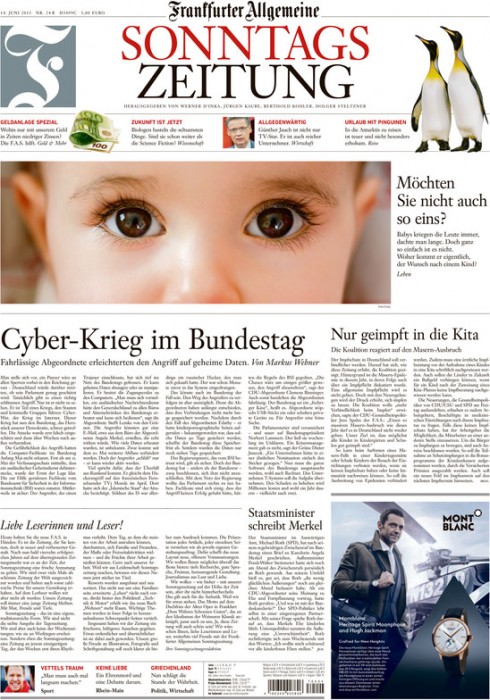
»Herrschaftliche Serifen« – neues Layout der FAS
Neues Layout bei der FAS
»Herrschaftliche Serifen« nennt die Süddeutsche online das, was das neue Layout der Frankfurter Allgemeine Sonntagszeitung ausmacht. Dieses stellte sich mit der heutigen Ausgabe zum ersten Mal dem kritischen Blick seiner Leser und für die Süddeutsche-Redaktion ist die visuelle Erneuerung ein »ansehnlicher Beitrag zur praktischen und geistigen Inneneinrichtung der Mittelklassen.«
aus der »Süddeutsche«: Wenn Zeitungen und Zeitschriften heute neben den digitalen Vertriebswegen auch als Print-Produkt weiterleben wollen - was gar nicht so unmöglich ist, wie man in den Anfangsjahren des Internets dachte -, dann müssen sie die praktischen und ästhetischen Vorzüge von Druck und Papier stärker herausstellen.
Das sieht man mittlerweile bei vielen Blättern am Design: Die Auftritte von Texten, Fotos, Grafiken werden großzügiger, zugleich wird die Buchstabenhaftigkeit stolz hergezeigt. Mitunter fällt das etwas übertrieben aus - jede einzelne Letter prunkt dann mit herrschaftlichen Serifen, und die Initialen am Textanfang werden so groß wie in mittelalterlichen Prachthandschriften.
aus der »FAZ«: Die schönste Zeitung der Welt soll noch schöner werden. Mit diesem Anspruch startet die vielfach preisgekrönte Frankfurter Allgemeine Sonntagszeitung in die nächste Ära und stärkt dazu ihre Sonntagskompetenz: Aktuelle Informationen, scharfsinnige Analysen und kluge Unterhaltung. Die optisch wie inhaltlich überarbeitete Sonntagszeitung erscheint erstmals am 14. Juni 2015 und bietet neue Sichtweisen, Inspiration, Niveau.